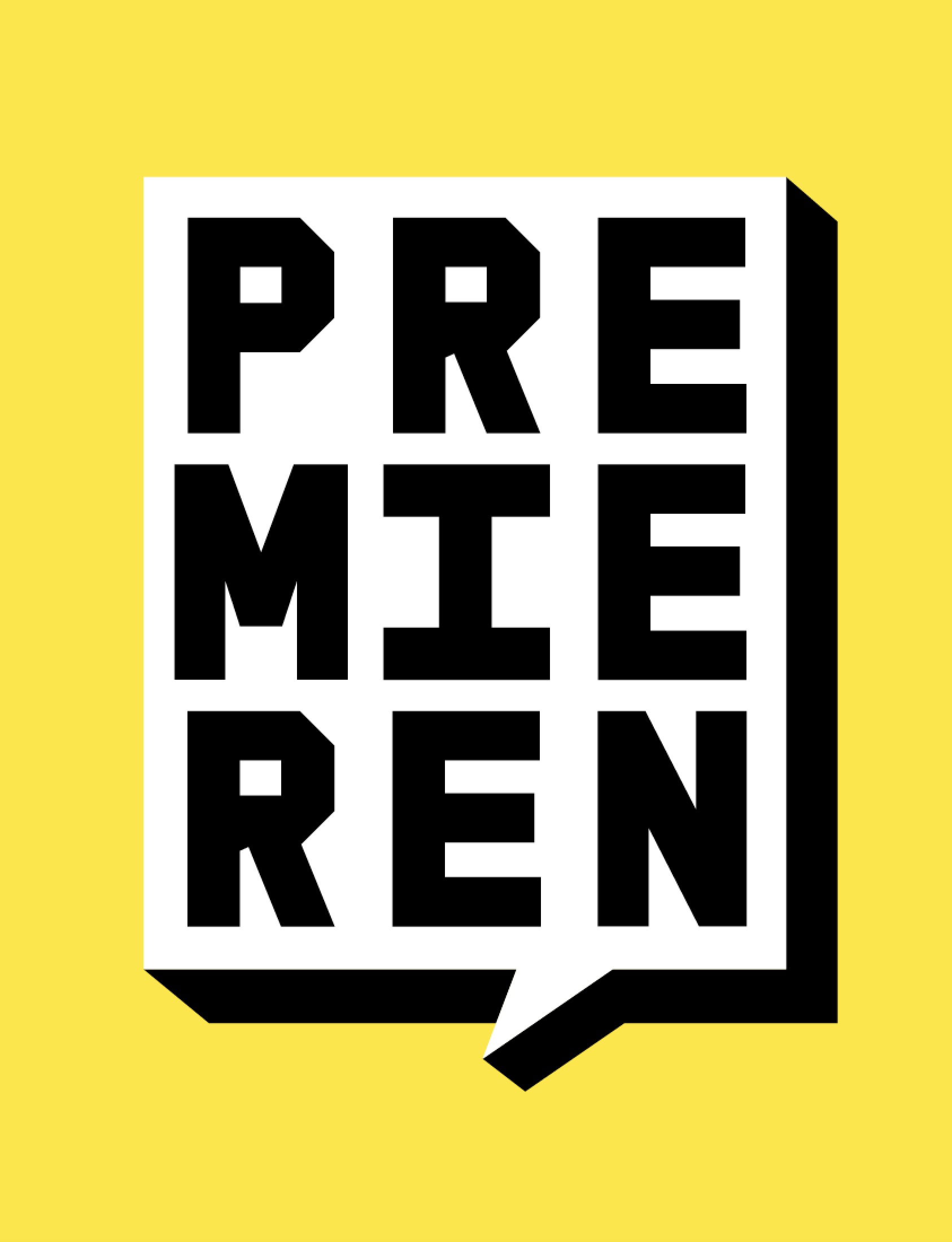
Type out loud
Buchstaben können einer Marke ein unverwechselbares Gesicht geben – ein Hoch aufs Typographic Branding!
Das Display unseres Smartphones zeigt jede Menge bunter Bilder und Icons, die um unsere Aufmerksamkeit buhlen. Buchstaben begegnet man eher selten. »Dabei ist Schrift, richtig eingesetzt, in der Lage, die Persönlichkeit einer Marke zu bestimmen «, sagt Leonid Fishman, Gründer von Strive Collective in Hamburg. »Gerade in einer mit Symbolen übersättigten Welt kann Typo abgrenzen, inspirieren, politisch sein und eine Botschaft emotional aufladen.« Strive ist ein auf Digital Branding und Innovation spezialisiertes Freelancerteam, das im Auftrag von Unternehmen und Agenturen Produkte und Marken entwickelt. Die sechs Designer gaben zum Beispiel funk, dem Online-Medienangebot für ein junges Publikum von ARD und ZDF, ein frisches Gesicht.
Die Stärken von Schrift als Branding-Tool liegen auf der Hand: Sie ist schnell erfassbar, funktioniert medienübergreifend auch auf kleinen Screens und lässt sich durch alle Kanäle und Touchpoints einer Marke spielen. »Allerdings will sie immer auch gelesen werden«, erklärt Leonid Fishman. »Ein Bild geht einen direkteren Weg in der Wahrnehmung. Eine gute, prägnante Bildmarke kann man unter Abertausenden von Symbolen in Sekundenbruchteilen wiederkennen.« Schrift wiederum hat den Vorteil, dass sie sich durch den gesamten Webauftritt zieht und nicht nur – wie viele Bildmarken – auf der Startseite präsent ist.
Staatsschauspiel Dresden
And Go
Flyer
Kampagne
Now is the time of Monsters
Free Music
Schools of Tomorrow
Wörterbuch der Gegenwart
Pinakothek Bayerische Staatsgemäldesammlungen
Pink Floyd